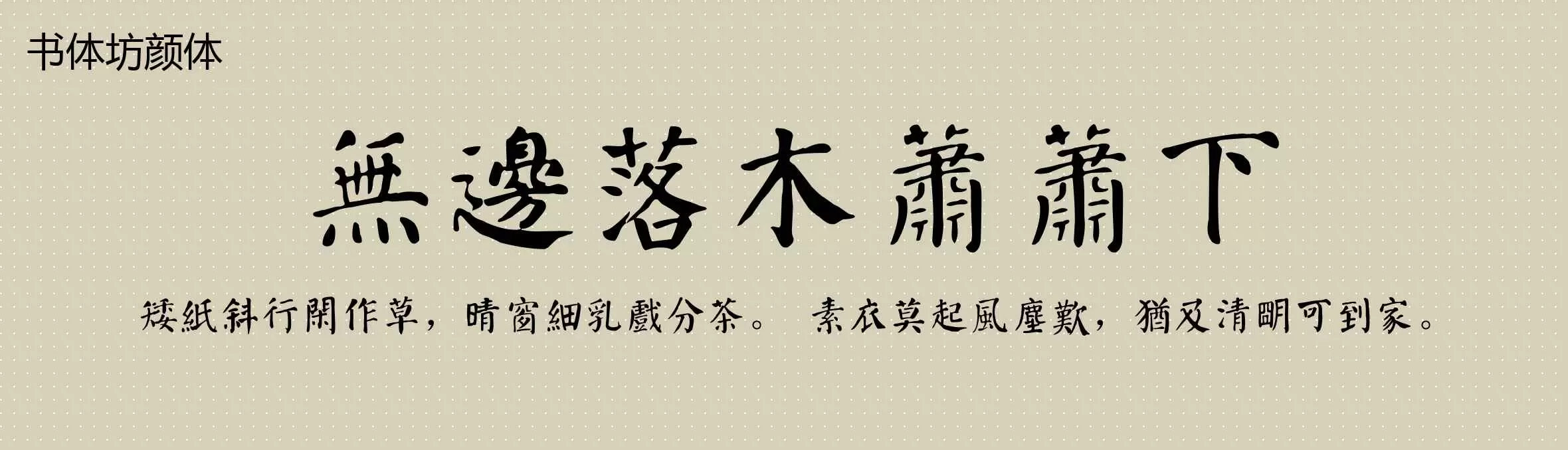
书体坊颜体是一款非常流行的中文字体,它的设计灵感来源于古代的铜板印刷字体。书体坊颜体的特点是线条流畅、笔画粗重、布局美观大方,非常适合用于标题、标志、广告等场合。此外,书体坊颜体还有多种字体格式可供选择,包括常规、加粗、斜体等,能够满足不同场合的需要。总的来说,书体坊颜体是一款非常值得推荐的中文字体。